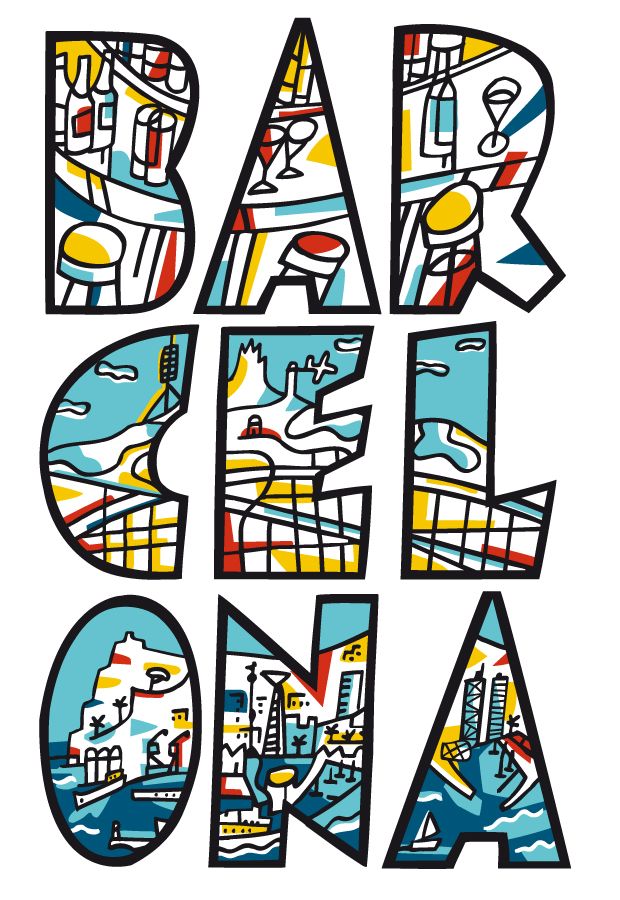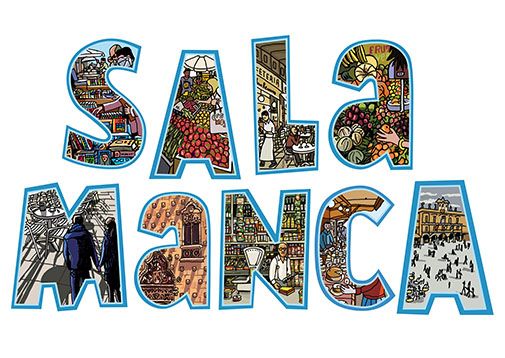
Plagio descarado
En esto del diseño hay veces que uno copia un poco al de al lado o simplemente se inspira, pero ante semejante plagio una no puede dejar de preguntarse dónde está el límite.
No hace falta que añada mucho más, juzguen ustedes mismos éste diseño de cartel de un estudio llamado "El cohete amarillo"
La tipografia de "BARCELONA" es un diseño original de MARISCAL, el cartel de UTRERA es del susodicho estudio gráfico.
Que vaina. :/
Habrán visto que Mariscal está en la ruina y habrán pensado "no tendrá dinero para demandar".
el otro dia vi en valencia uno igual, con val en cia
uf la verdad que no se ha cortado mucho con en el plagio.. SON IDENTICOS!
Pues al final lo que vi no era un plagio, sino un autoplagio de mariscal, que se ve que el hombre esta hecho polvo y aurrinado
La comparacion con el original es tristisima
Versión de la campaña del Sabadell en Salamanca...en carteles he visto la versión "Sal__ama__nca"
Pues que lastima si el hombre tiene que recurrir a destrozar asi su propio trabajo, porque el resultado es de vergüenza ajena.
Casi lo leo
"UT
RE
RA"
wtf?!
Duele leerlo.
Lo del plagio, mira, cada uno sabe lo que hace, es descarado, yo diría que denunciable, pero allá cada uno con su conciencia.